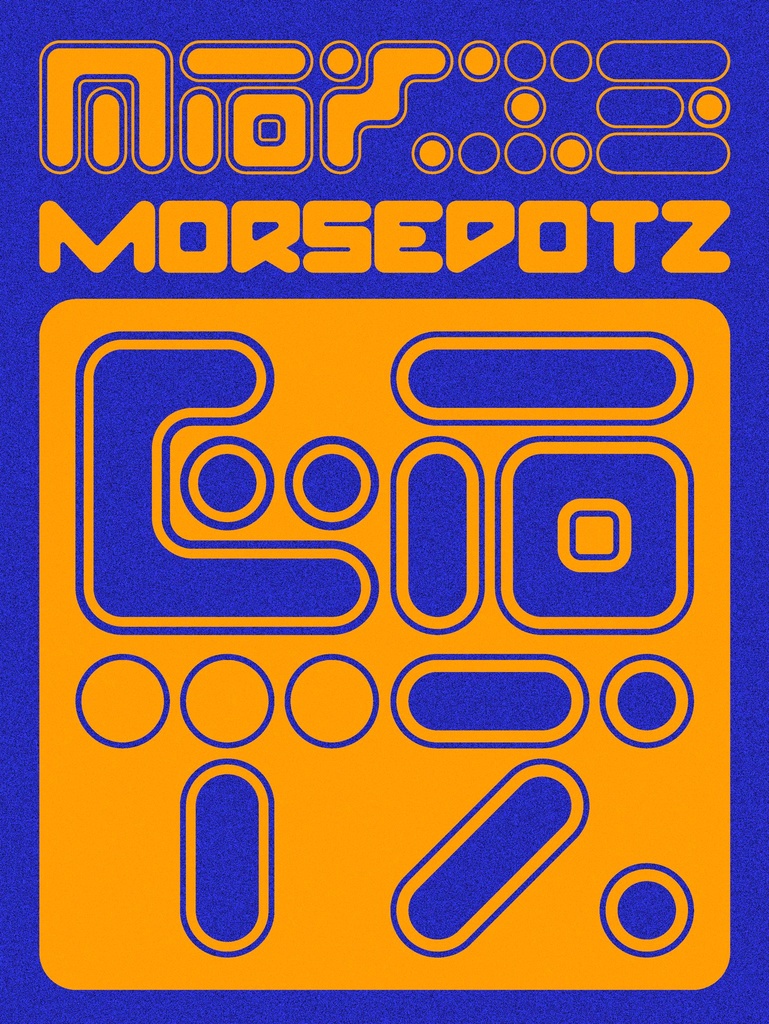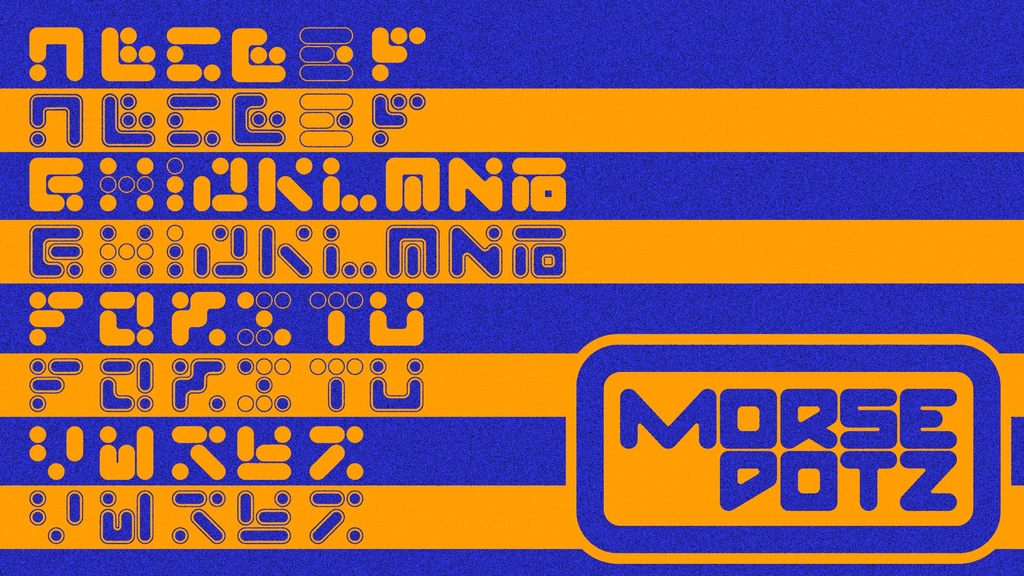
MorseDotz Font
モールス信号のアルファベットパターンを無理やり文字にしました。 出来るだけ近づけましたが可読性は壊滅的なのでエイリアン文字などSFフィクション文字として使うことができます。 ちなみにこの表記通りに打つとちゃんと符号になります。 教育目的にもなりますね。やったあ OTFとTTFの両方が中に入っています。 なお フォントを見ながらモールス信号を打つとき どれだけ長かったり、曲がりくねっていても(RやWなど) 打つときに伸ばす長さは変わらなかったりします。 あとついでに気分でイラレデータへの共有リンクのメモもぶち込んでおきました。 This is a Morse code alphabet pattern that I made into letters. I tried to make it as close as possible, but the readability is not so good, so you can use it as alien characters or other SF fiction characters. By the way, if you type the letters as they are written, they become signs. It can also be used for educational purposes. Yay! Both OTF and TTF are included in the package. In addition, when you type Morse code while looking at the font It doesn't matter how long or crooked the letters are (R, W, etc.) When you type, the length of the line remains the same. I've also included a note about sharing links to the Illustrator data. Have fun! !!!!UPDATE!!!! 今更 大文字と小文字と数字を追加したよ あとフォント名に”UED“の統一英単語三文字が追加されたよこれでこの先リリースされるフォントと区別できるよやったねたのしんでね! 書くの忘れてたけどこのフォントは100%FREE!!! でもよかったら使ったコンテンツのURLとか送ってくれると嬉しかったりするよ! なお、このフォント使って何かトラブルが起きても私は一切責任取りません ご了承ください。 I've added upper and lower case letters and numbers now. Also, we've added the three letters "UED" to the font name to distinguish it from other fonts we'll be releasing in the future. Have fun! I forgot to mention that this font is 100% FREE! But I would be happy if you could send me the URL of the content you used! Also, I'm not responsible for any problems that may occur using this font. Please understand.